Aprende árabe con la tipografía de Rami Hoballah
El principal uso de las tipografías es comunicar un mensaje a través de diferentes caracteres; el diseñador gráfico libanés Rami Hoballah nos muestra que también pueden aportarnos conocimientos como aprender un nuevo idioma. Por medio de una serie de palabras en árabe con una tipografía creada por él mismo, nos muestra su correcta escritura.
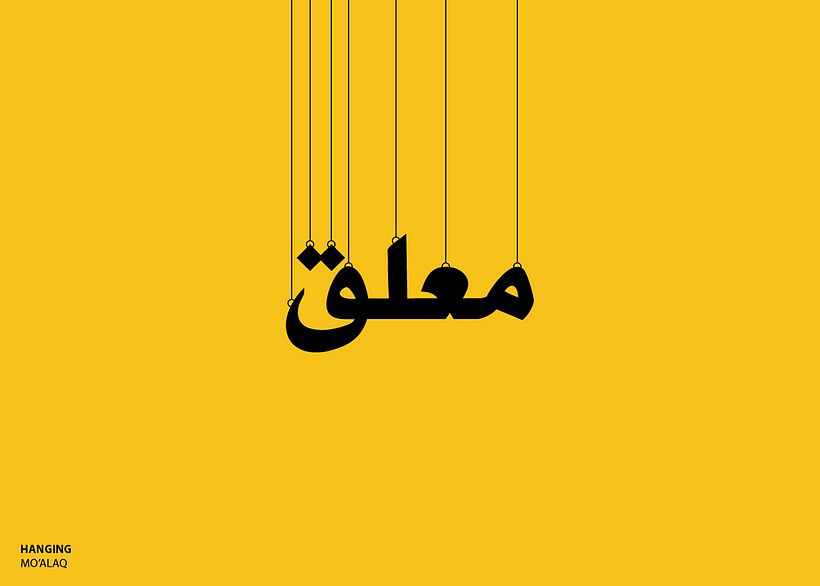
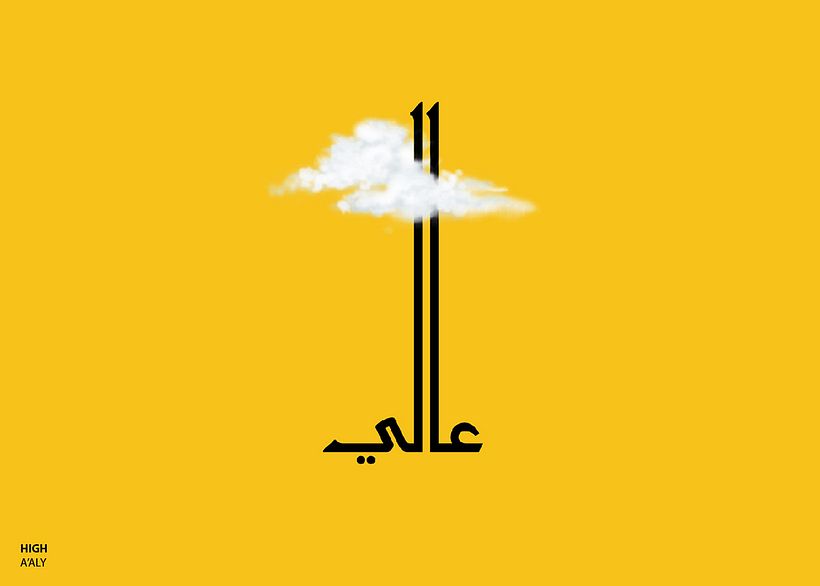
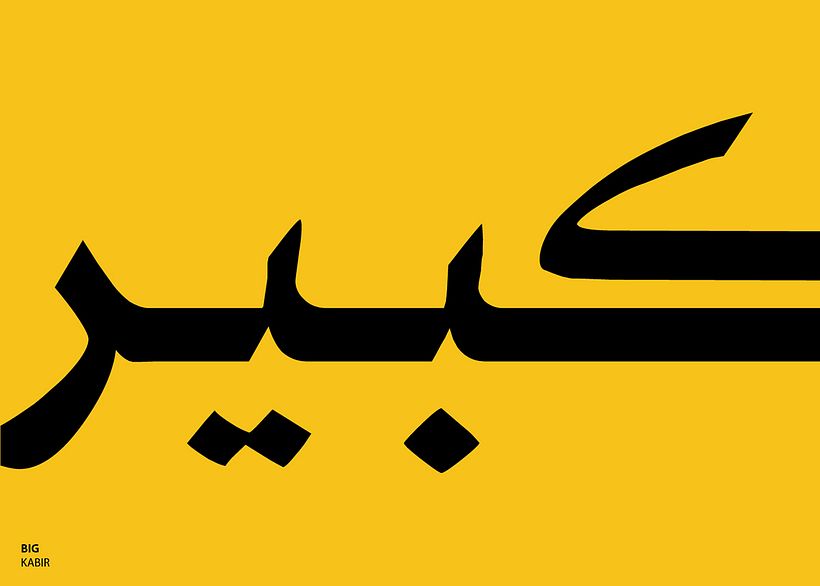
Rami Hoballah ha dedicado buena parte de su tiempo libre a desarrollar proyectos que ayudan a introducir palabras, términos e incluso películas, marcas y personajes de la cultura occidental a la oriental por medio de diferentes tipografías.
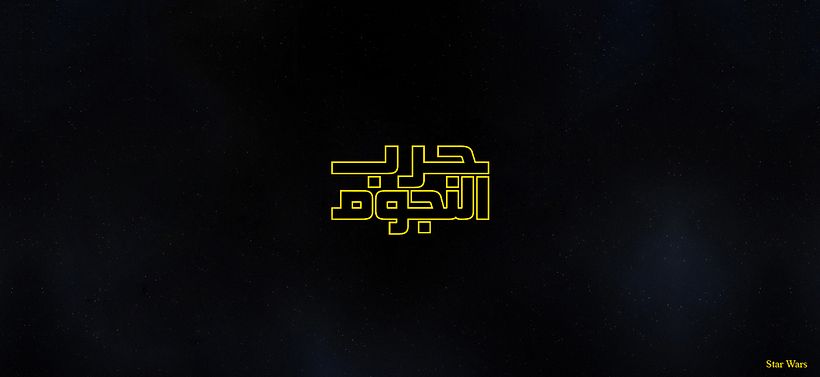
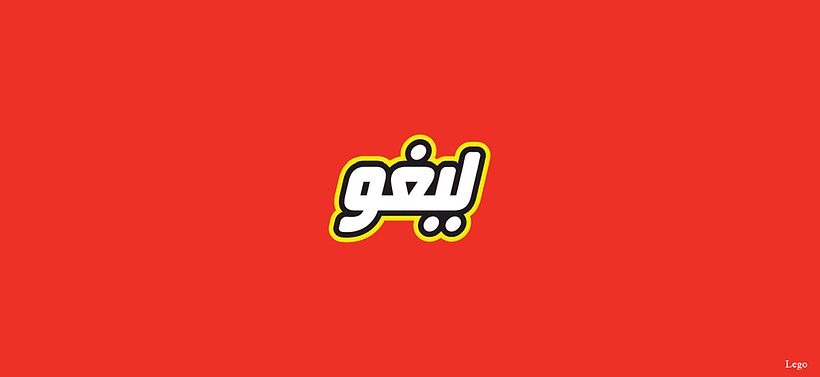
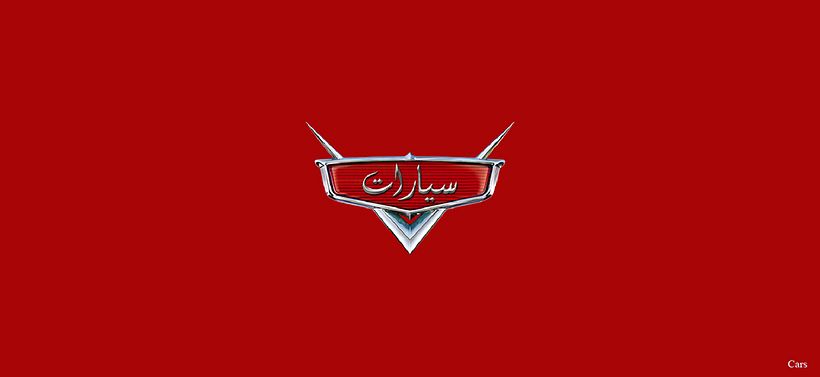
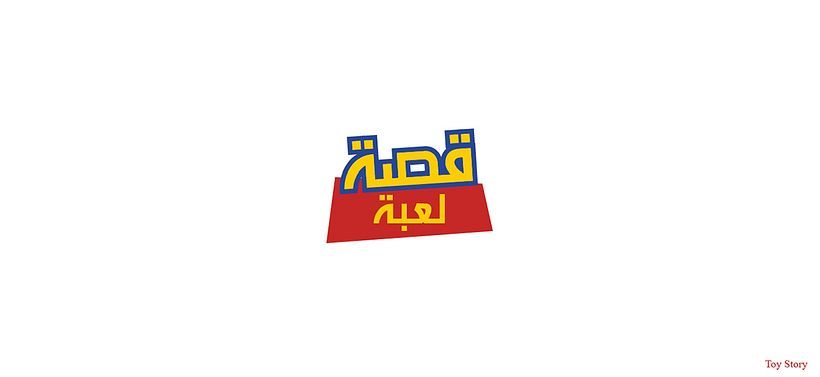
El proyecto de este estudiante destaca por su creatividad, pero sobre todo porque en países como India o Kuwait el diseño gráfico no es tomado como una primera elección de carrera por muchos estudiantes. A diferencia de España, México o Colombia (entre otros de habla hispana) donde el diseño es parte de nuestro día a día, en estos lugares en específico no tiene tanto impacto, por lo que cada proyecto que hace cada estudiante, es un logro para la comunidad creativa de su localidad y del mundo.